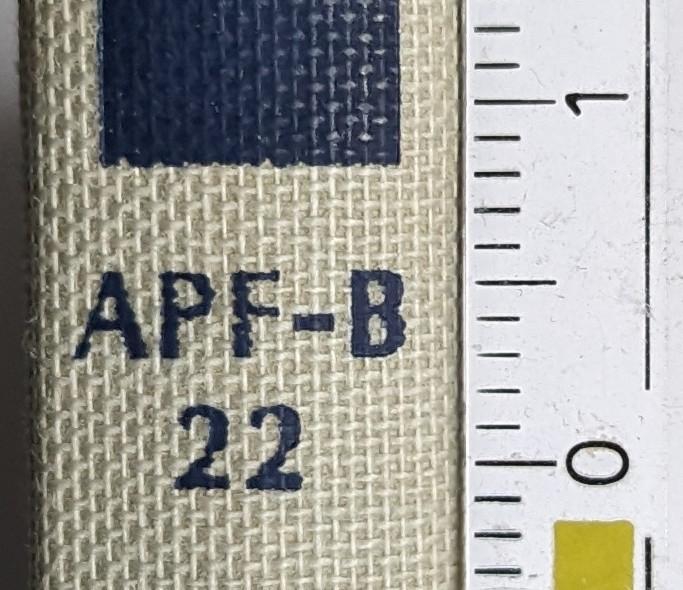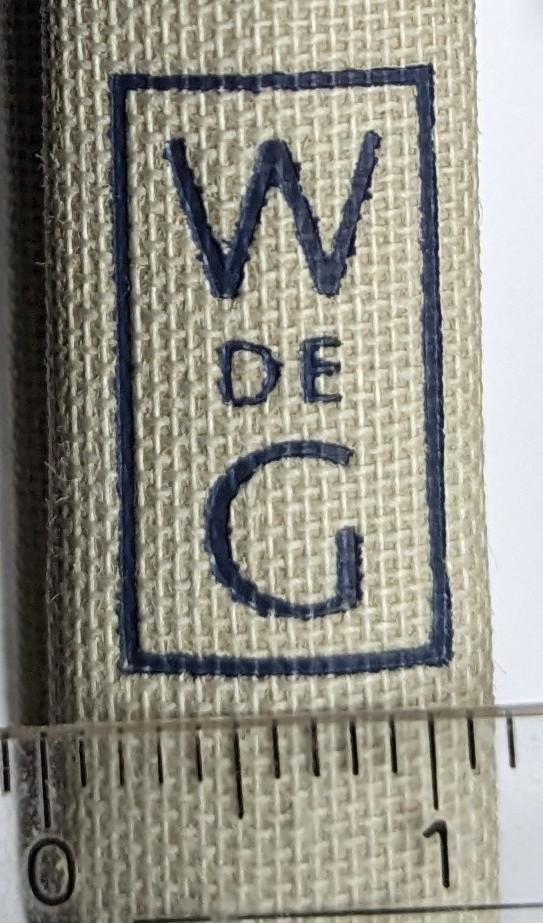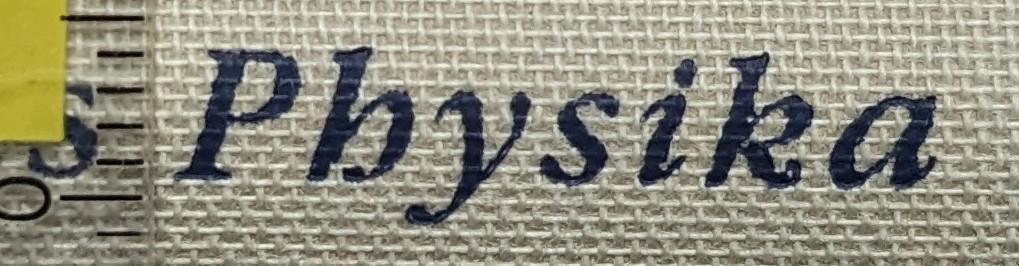
Auch bei Verwendung eines Titling-Font Glyphen in jedem Fall »ohne Berührung« setzen?
Ich verwende für eine Prägung auf einem Cover einen Titling-Font, bei dem das »R« nach rechts hin deutlich verlängert ist und ohne manuelles Kerning i. d. R. den nachfolgenden Glyphen berührt (siehe Screenshot).
Es gilt ja generell als Regel, dass sich einzelne Glyphen nicht berühren sollen. Allerdings ist es bei diesem Font ja ein bewusstes Stilmittel, dass das »R« weit nach rechts ausläuft. Und wenn ich die nachfolgenden Buchstaben entsprechend durch Kerning nach rechts verschiebe, stehen die beiden Buchstaben, im Ganzen, relativ weit voneinander entfernt.
In diesem speziellen Fall ist es, wie bereits erwähnt, zudem so, dass es um eine Prägung auf Gewebeeinband geht, wo ein bloß minimaler Zwischenraum zwischen den Glyphen ggf. ohnehin nicht funktionieren würde. Eventuell müsste man ihn daher hier etwas großzügiger anlegen.
Wie seht ihr das? Würdet ihr auch in einem solchen Fall ein entsprechendes Kerning vornehmen, so dass die Glyphen sichtbar getrennt voneinander gesetzt sind?
Das würde ich nicht anhand einer Regel, sondern nach Augenmaß entscheiden. Insofern stell doch bitte mal ein Beispiel mit mehr Spationierung zwischen R und I ein.
Die beste Lösung wäre sicher eine so große Sperrung, dass das Problem gar nicht mehr auftritt. Bei Versalsatz kann man da ja recht weit gehen.
Ansonsten wird man irgendeinen Tod sterben müssen. Berührungen grundsätzlich zu vermeiden, ist keine Regel. Es kann das kleinere Übel sein, wenn die Zwischenräume ansonsten zu groß werden.
Schon so wie jetzt gesetzt bettelt das „i“ nach etwas Distanz zum „r“. Dem ganzen dann zusätzlich noch etwas mehr Leerraum verpasst würd ich jetzt nicht als störend empfinden wenn der „Friedrich" allein für sich steht.
Okay, hier mal drei Varianten …
Ich denke, mit Kerning ist wohl doch besser.
Die Schriftgröße ist ca. 14 pt, d. h. nicht übermäßig groß. Ich denke daher, dass es wahrscheinlich die dritte Variante werden müsste, da man den Zwischenraum sonst im geprägten Schriftzug vielleicht gar nicht sieht, weil er als Zwischenraum zwischen Prägeflächen womöglich zu schmal ist. (Leider muss man ja eine Gravur herstellen lassen, um das zu testen …)
Einen Alternativ-Glyphen gibt es nicht.
Zwiechen „i“ und „e“ vertrüge es wohl noch etwas Luft. Finde dass der Friedrich in der 3. Variante dann recht fesch daherkommt.
Ich würde auch die Variante 3 nehmen und zwischen D und R noch ein klein wenig was rausnehmen? Irgendwie ist da noch ein Loch.
Ist die Schrift denn fixiert? Um sowas könnte sich auch der Schriftgestalter Gedanken machen, diese expressiven Buchstaben haben ja immer Konstellationen die ungünstig ausfallen, und wenn man sowas macht, müsste man sich theoretisch auch um diese Fälle kümmern (Alternativ-Glyphe, generell angepasste Metrik bei Opentype-Versalsatz, ...).
Ich finde keine der Lösungen wirklich gelungen. Für so etwas wertiges wie eine Prägung würde ich die Schrift nicht im Versalsatz nehmen, wenn es kein alternatives R gibt. Oder noch mehr sperren.
Ja, ich habe die Schrift nicht selbst entworfen, sondern eine Lizenz erworben. Über unzureichendes oder schlechtes Kerning bzw. fehlende OpenType-Funktionalitäten wundere ich mich leider bei so einigen kommerziellen Fonts.
Zum einen handelt es sich um einen Titling-Font, der nur Versalien und Kapitälchen bietet, zum anderen steht das abgebildete Wort nicht alleine, sondern ist nur ein kleiner Teil der Cover-Beschriftung. (Es ist kein Buch über Friedrich II. Den gesamten Titel kann ich hier aber momentan nicht einstellen.) Wenn auf dem Cover nur »Friedrich« stünde, würde ich Dir zustimmen, dass man womöglich noch mehr sperren könnte. So, wie es in meinem Fall ist, müsste ich dann allerdings etliche Buchstaben-Kombinationen auseinanderziehen und es würde dann insgesamt überhaupt nicht mehr stimmig aussehen.
Magst Du uns mitteilen, um welchen Font es sich handelt? Vielleicht hilft die Info einigen weiter, Dir zu helfen.
Ach so, das hatte ich wohl vergessen zu schreiben: Ich habe mich bereits längst für die dritte Variante entschieden. Insofern ist eigentlich keine weitere Hilfe mehr erforderlich. Ich hatte quasi nur aus Höflichkeit noch auf die beiden Beiträge geantwortet, nicht, weil ich die Diskussion fortsetzen wollte.
Ja, man kann ein Buch wahrscheinlich auch in LKW-Plane, Silikon oder Marmor-Tafeln einbinden.
Wie gesagt, ich kenne die Sortimente. Ich hatte geschrieben, dass es "normalerweise" Papier/Karton oder Gewebe ist.